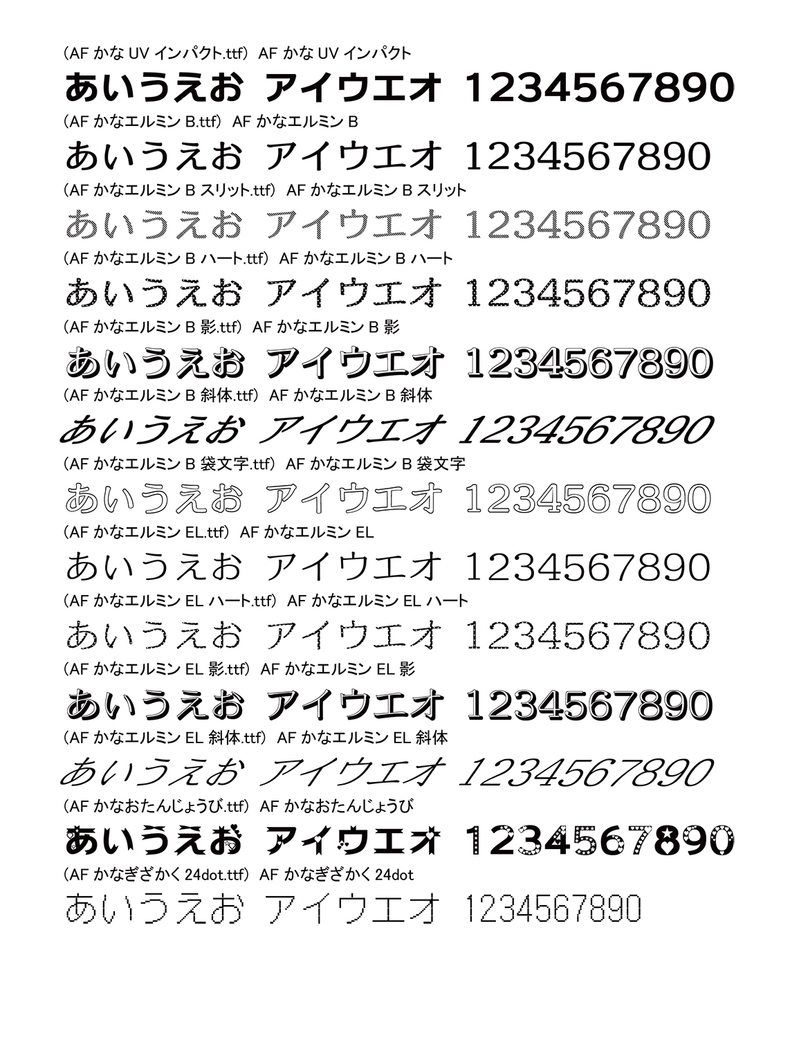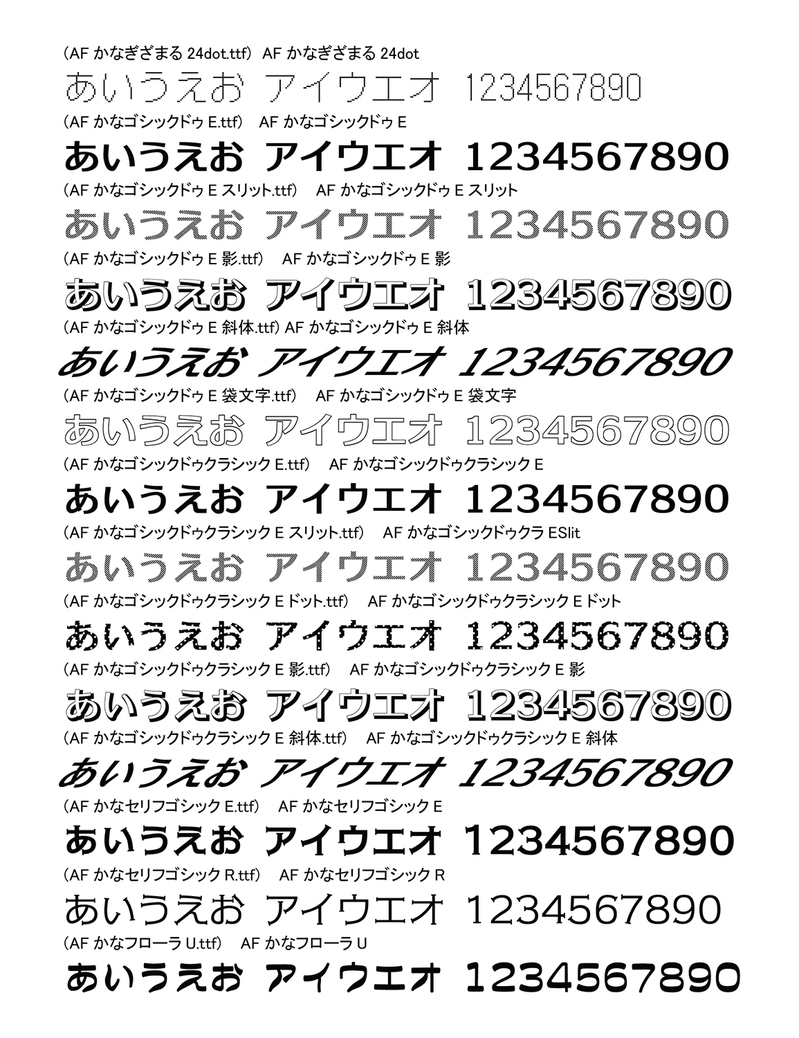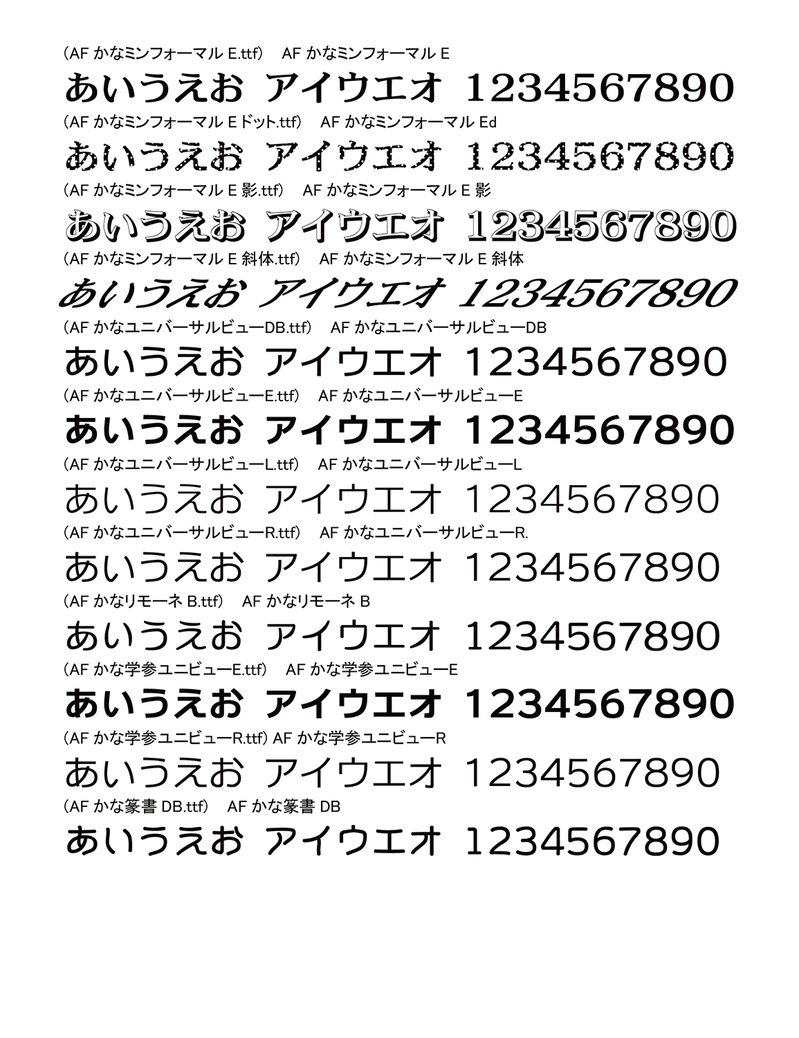
文字セット ひらがなカタカナ専用フォント
※プレビューフォントは「AFかなUVインパクト」です。
幼稚園・保育園のおたより(配布資料)に最適なひらがなカタカナ専用フォントです。販売済み和文フォントの中から斜体や袋文字など加工済みフォントなど 38書体と、新たに「AFおたんじょうび」を追加39セットでご案内です。
AFかな39set